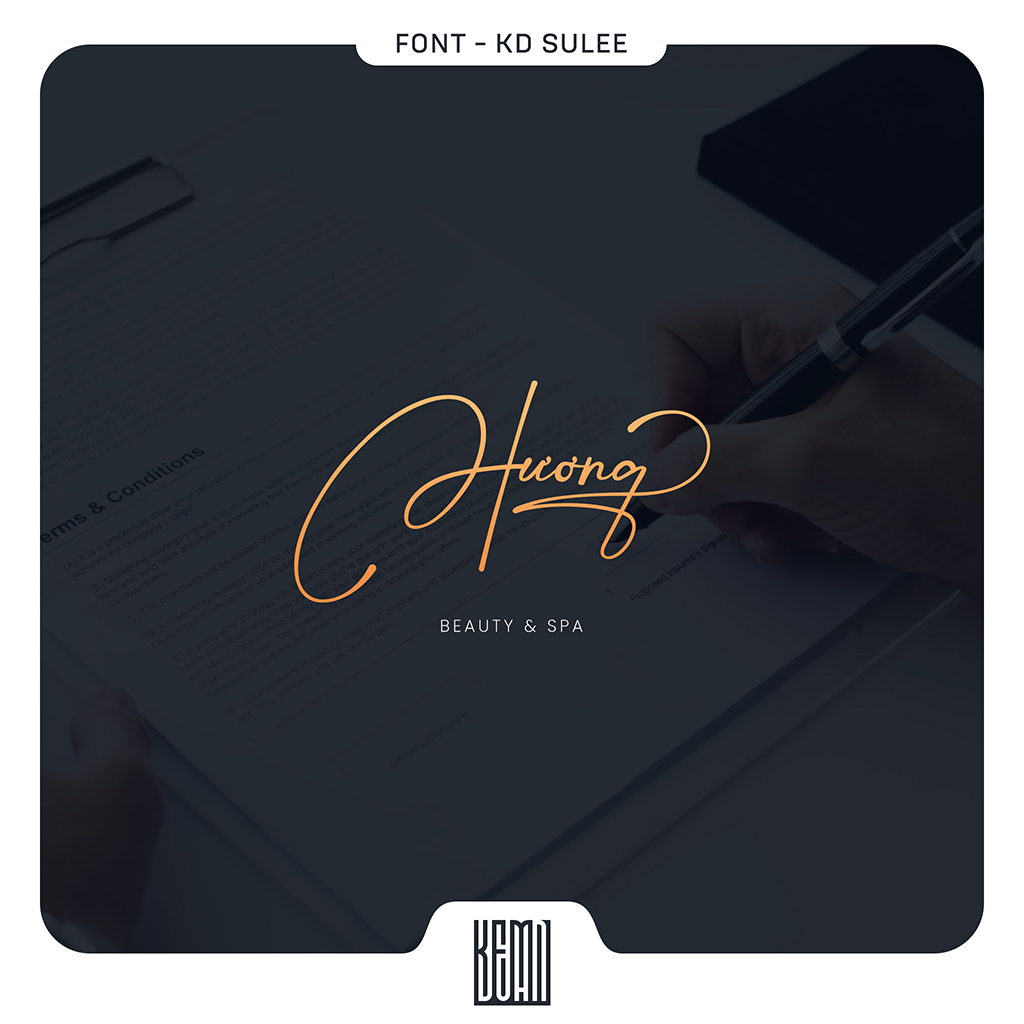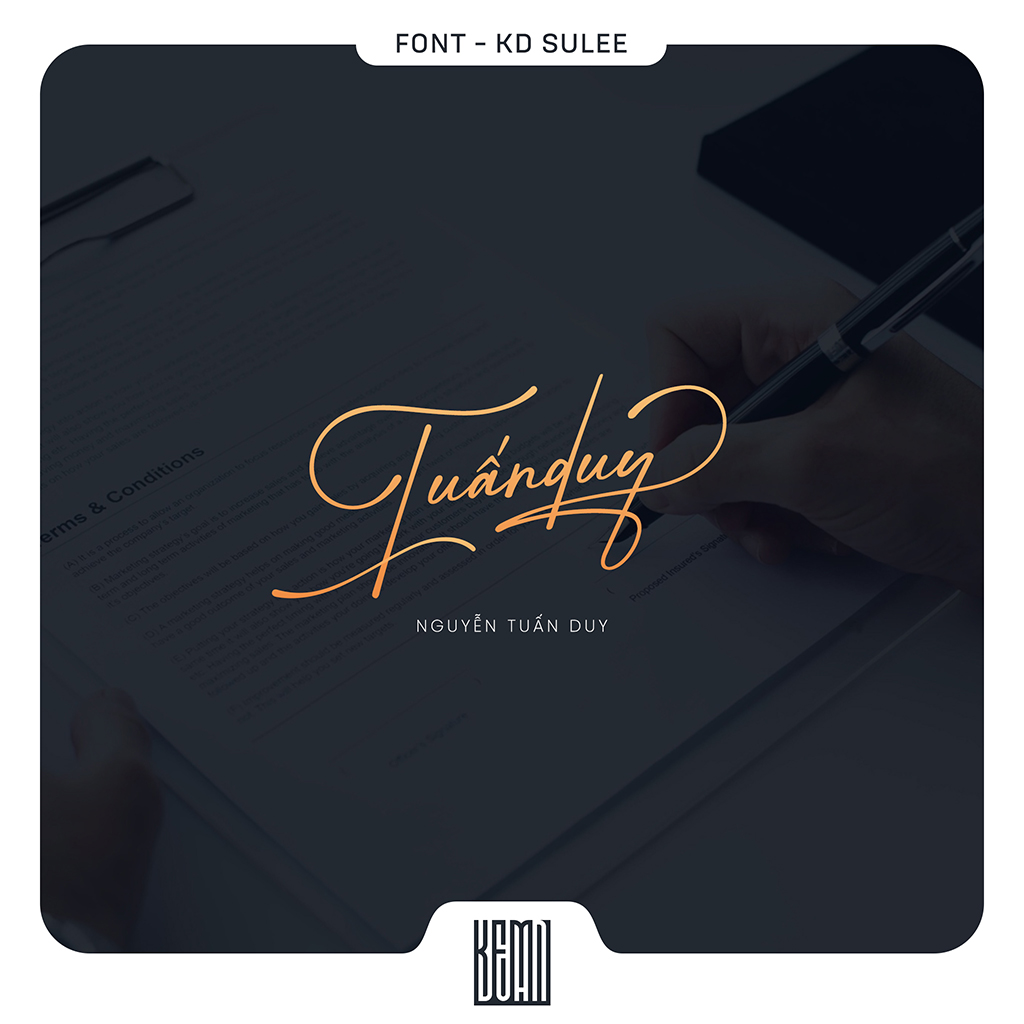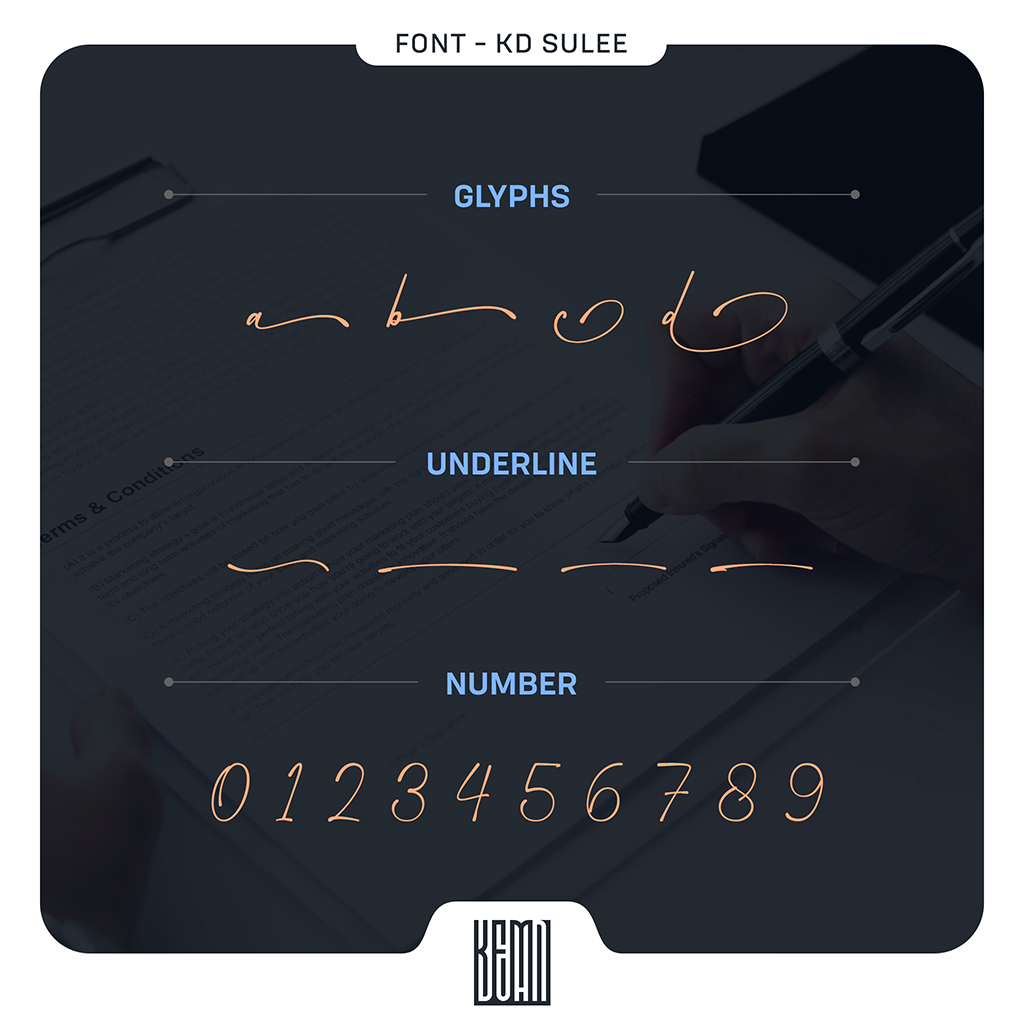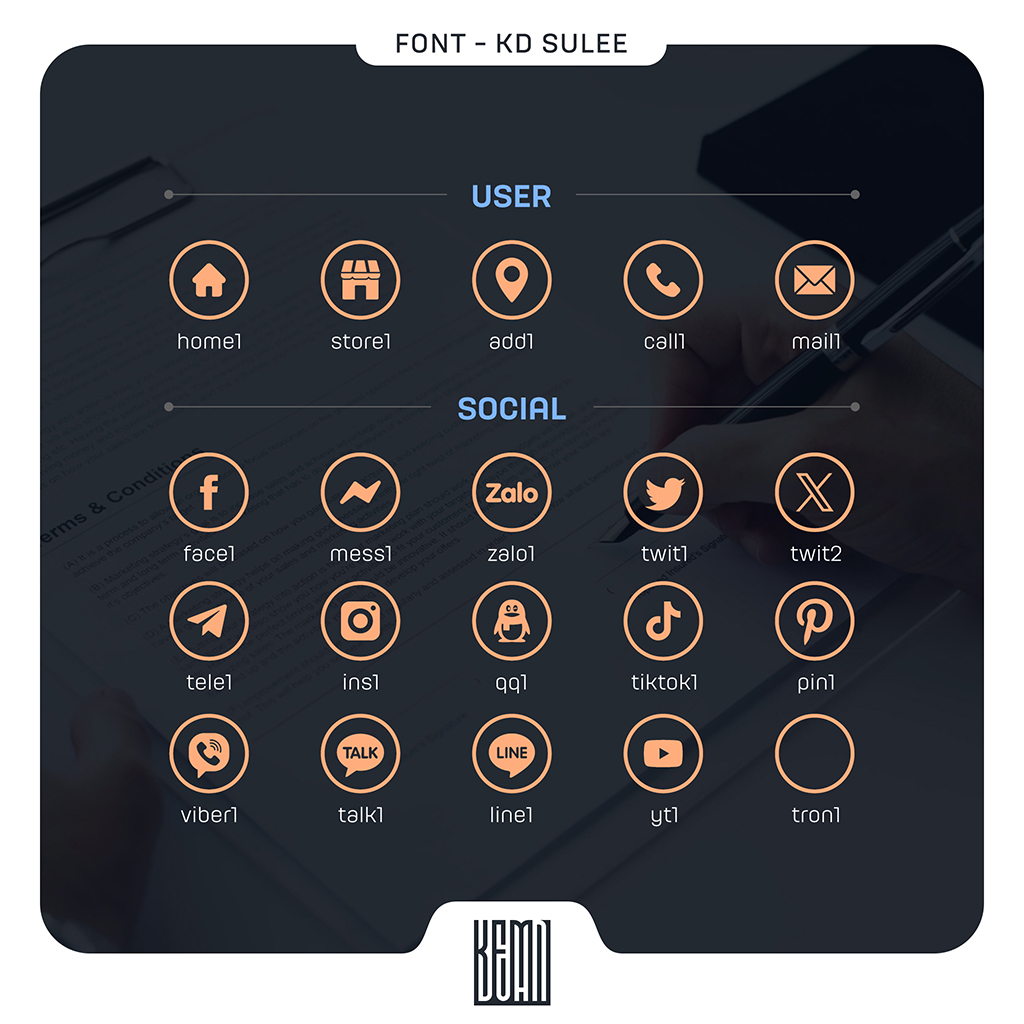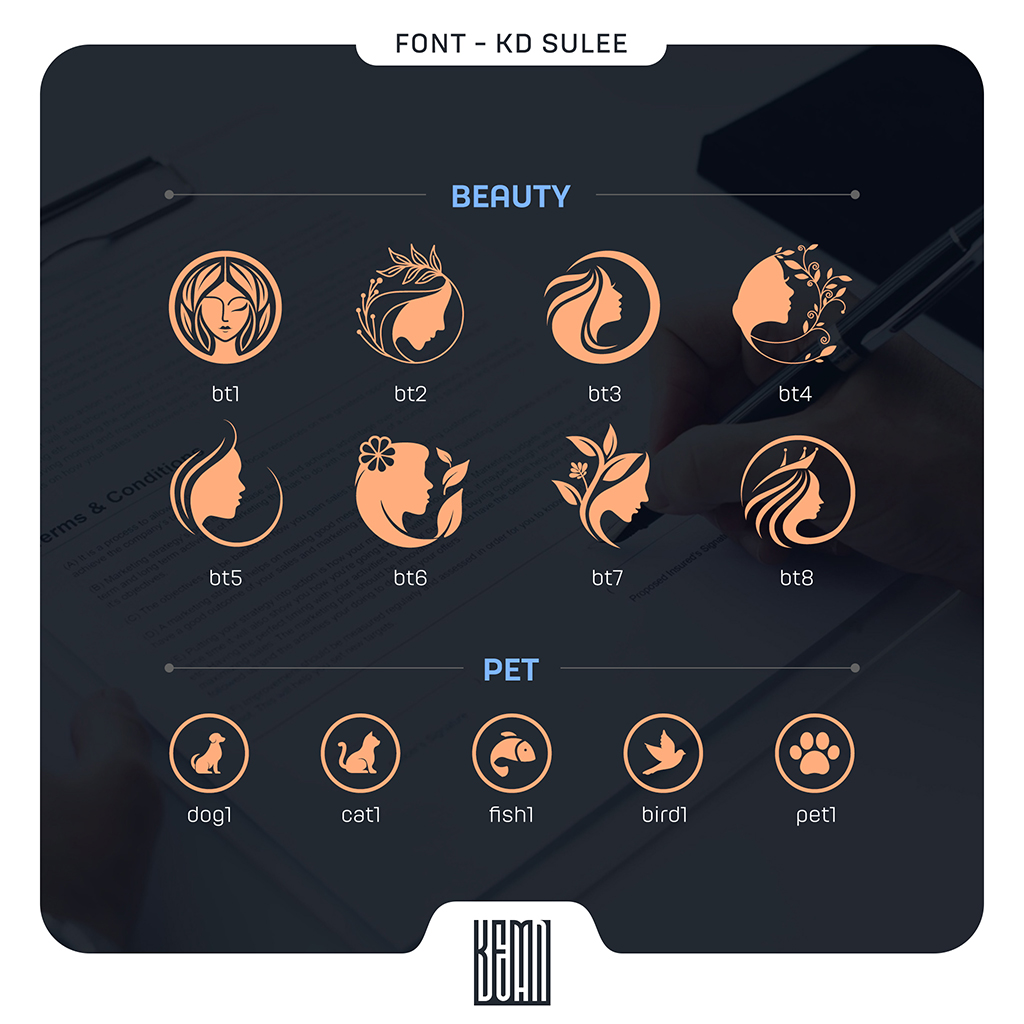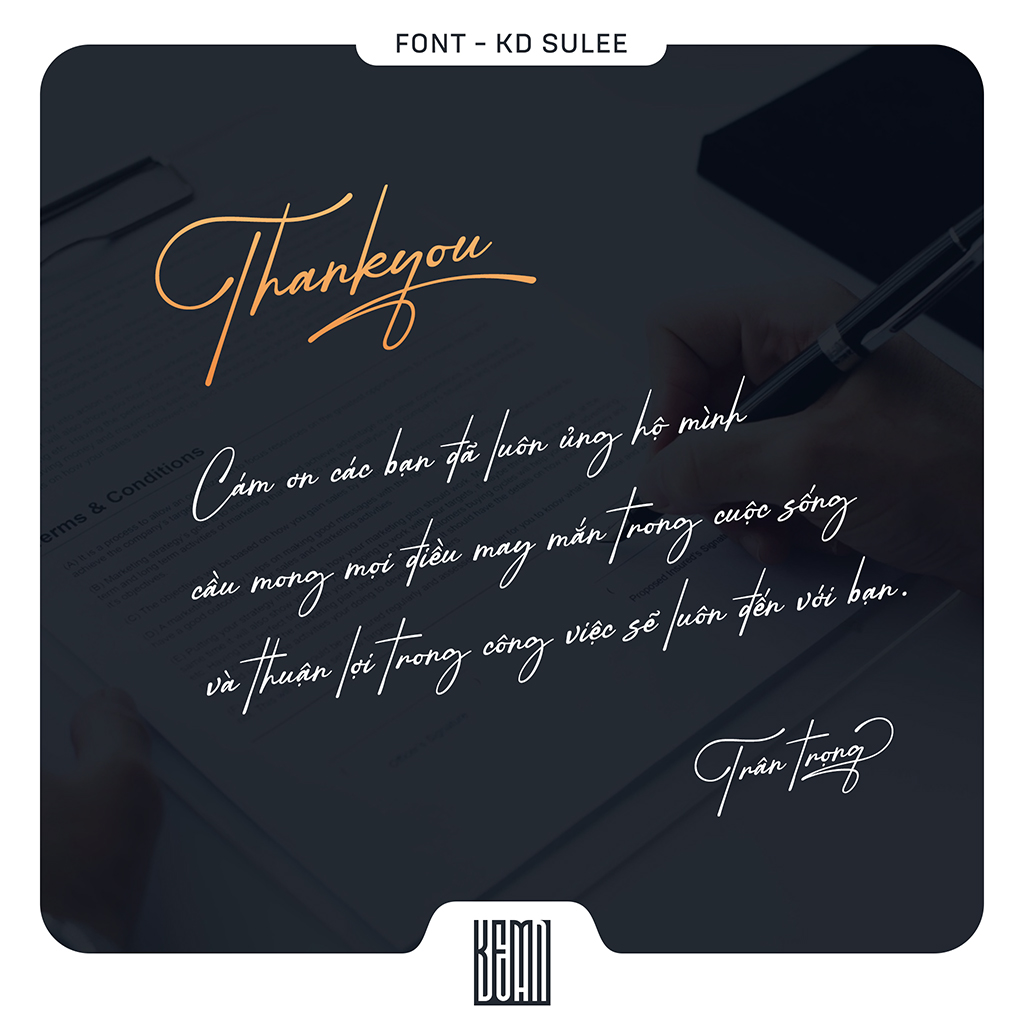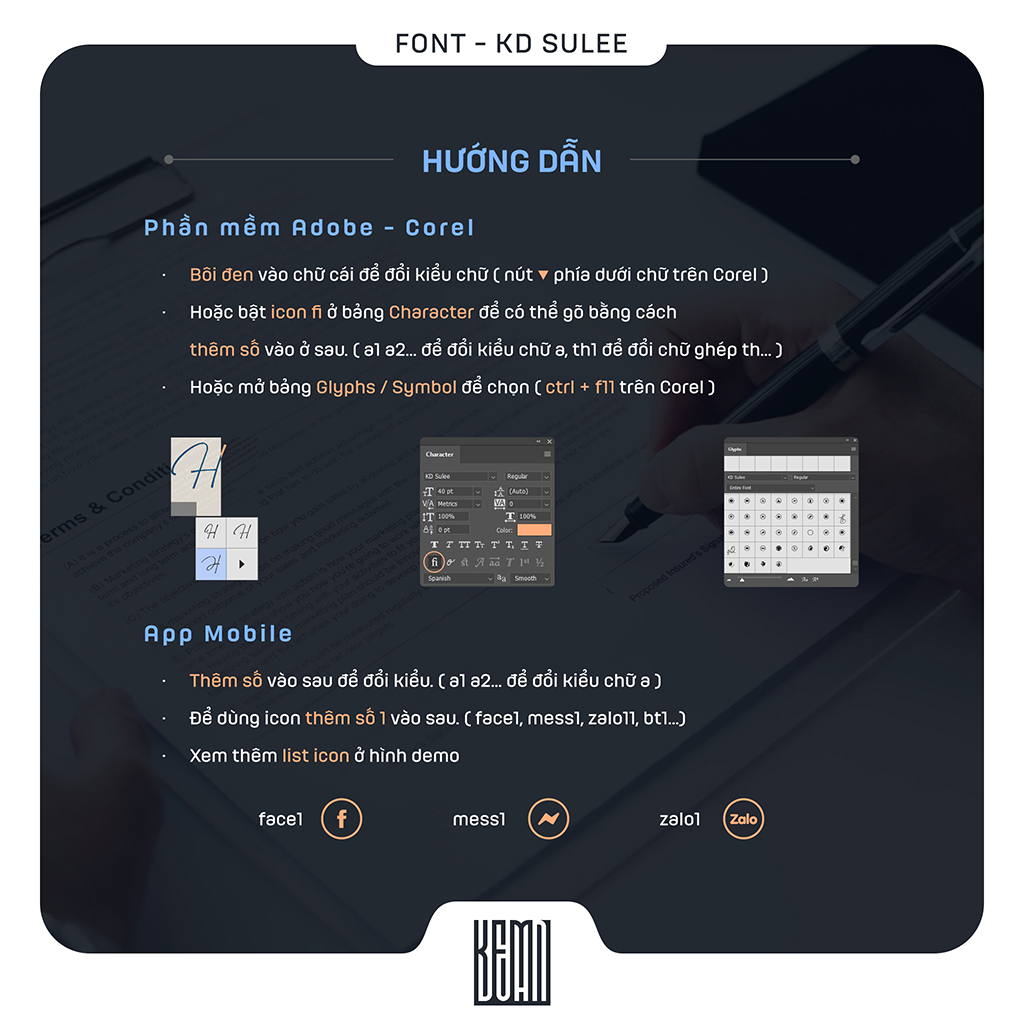
Font KD Sulee - Font chữ ký sang trọng
- KD Sulee là một font chữ ký sang trọng.
- Đặc biệt được thêm vào font rất nhiều icon với đủ nghành nghề rất thích hợp cho việc thiết kế Logo cá nhân, Beauty Spa hay Thiệp cưới.